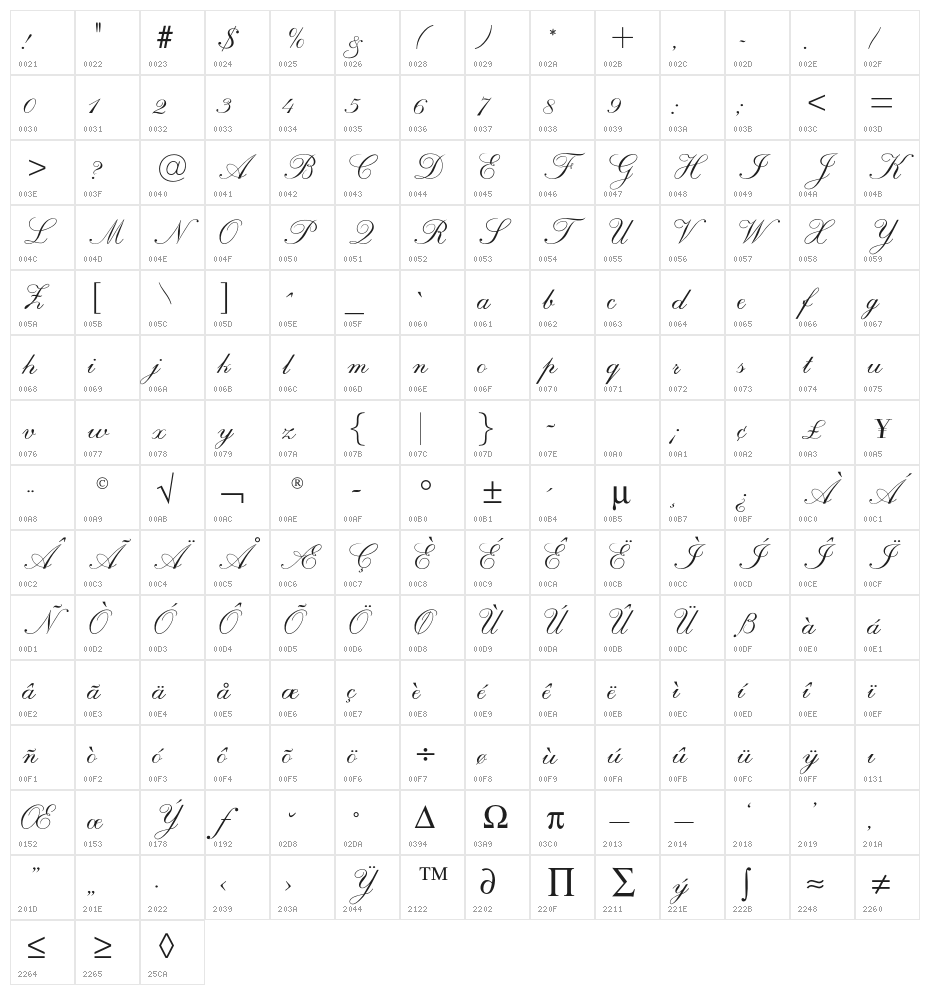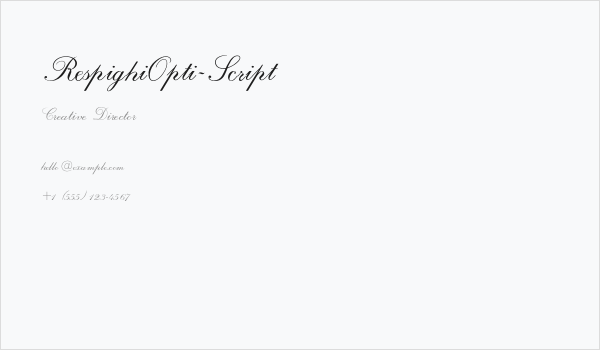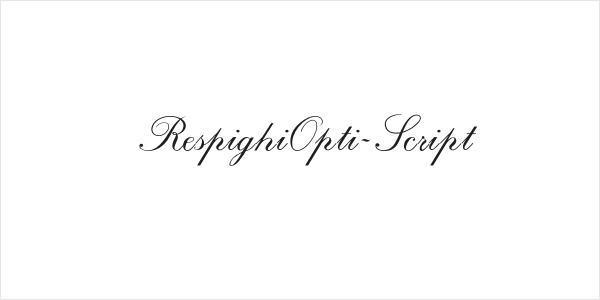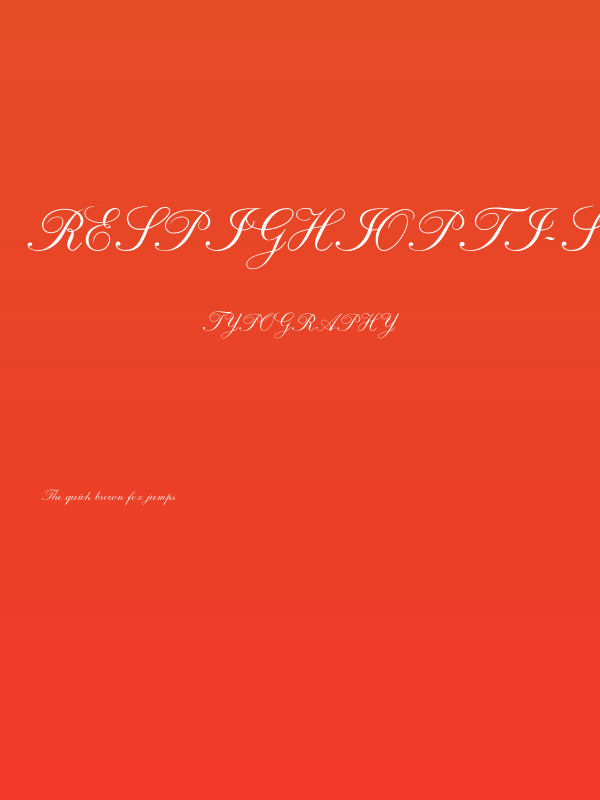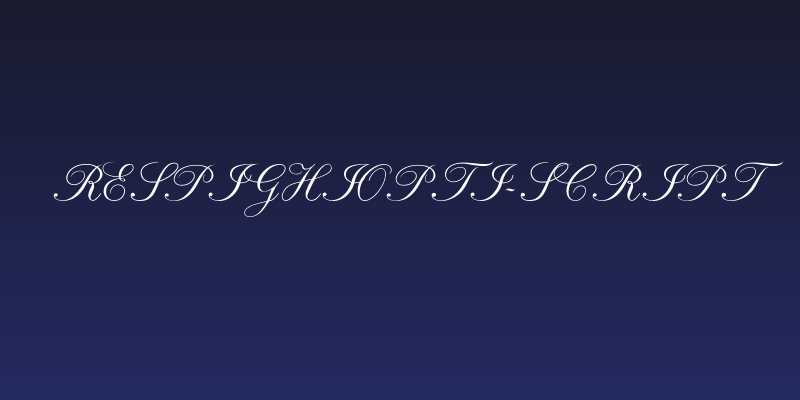
RespighiOpti-Script Font
| Gesamtstil | Elegant, Sophisticated |
| Anwendungsfall | Headlines, Invitations, Branding |
| Vorgeschlagene Projekte | Ideal for wedding invitations, formal event programs, elegant branding, and luxury product packaging. |